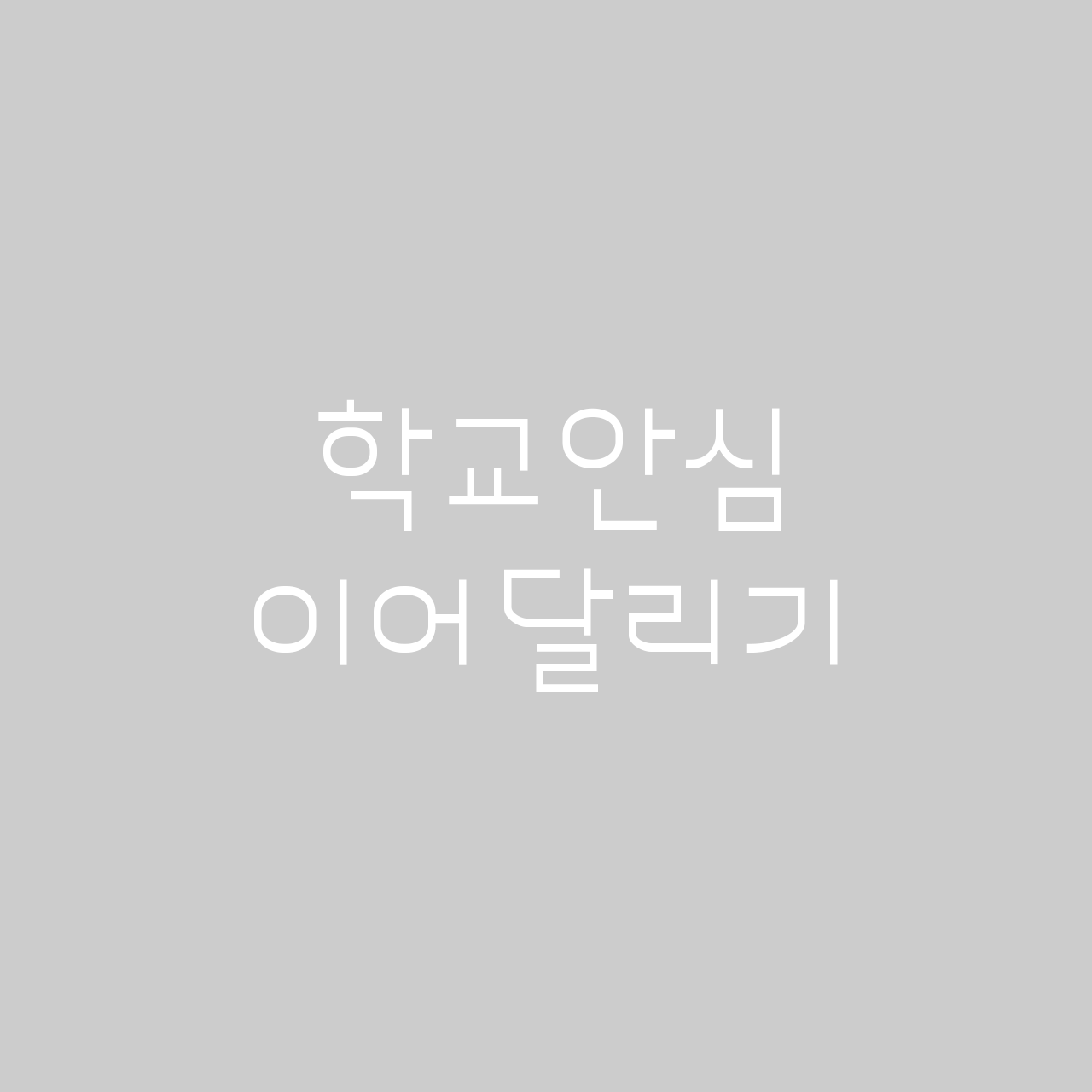
동그라미재단
동그라미재단 창립 5주년을 맞아 재단의 공유와 나눔 정신을 담은 “동그라미재단” 전용 서체를 개발하였다. 공유한다는 의미로 곡선의 획 형태를 표현해 부드럽고 따듯한 감성을 담았으며, 모음 ‘ㅇ’을 세로로 길게 디자인해 밝고 활기찬 에너지를 느낄 수 있다. 또한, 모듈을 상승시켜 초성 윗줄의 시각적 흐름을 정리하여 특징있는 제목과 단문 뿐만 아니라 긴 호흡의 문장을 작성하는데 적합하다.
- Sans,민부리